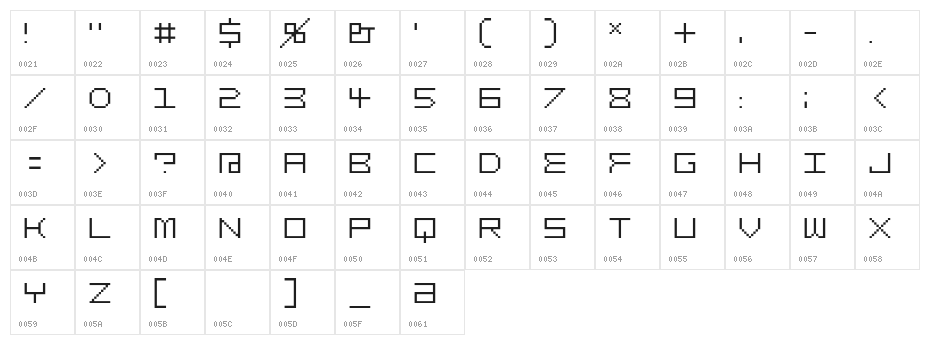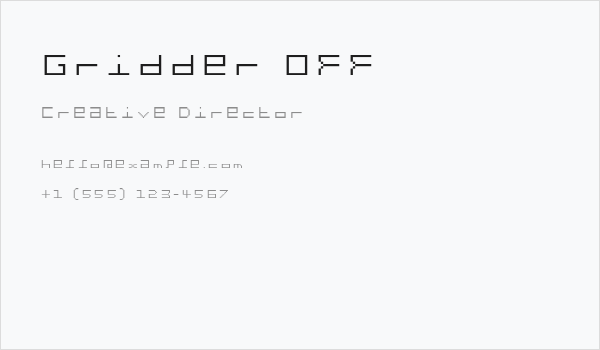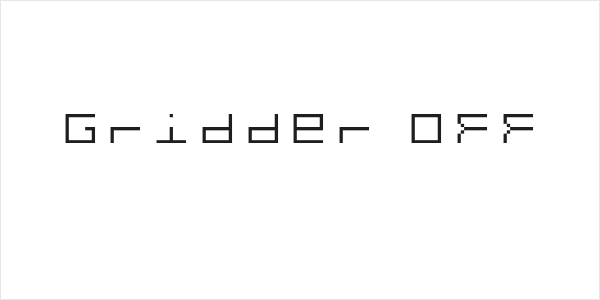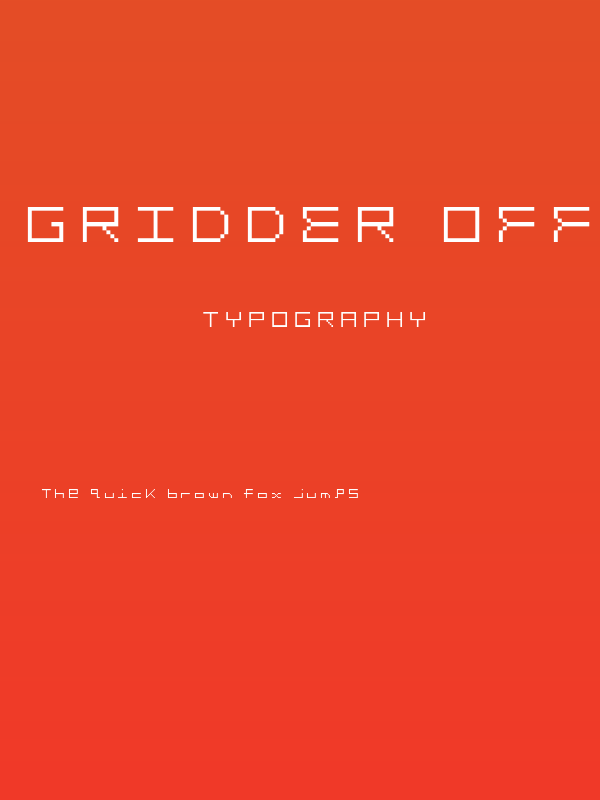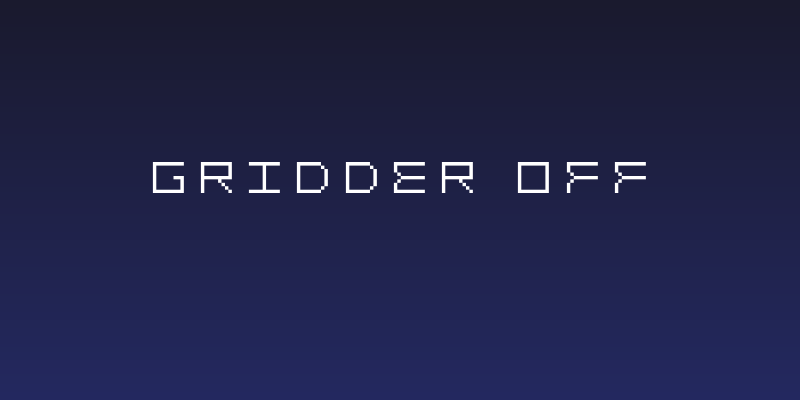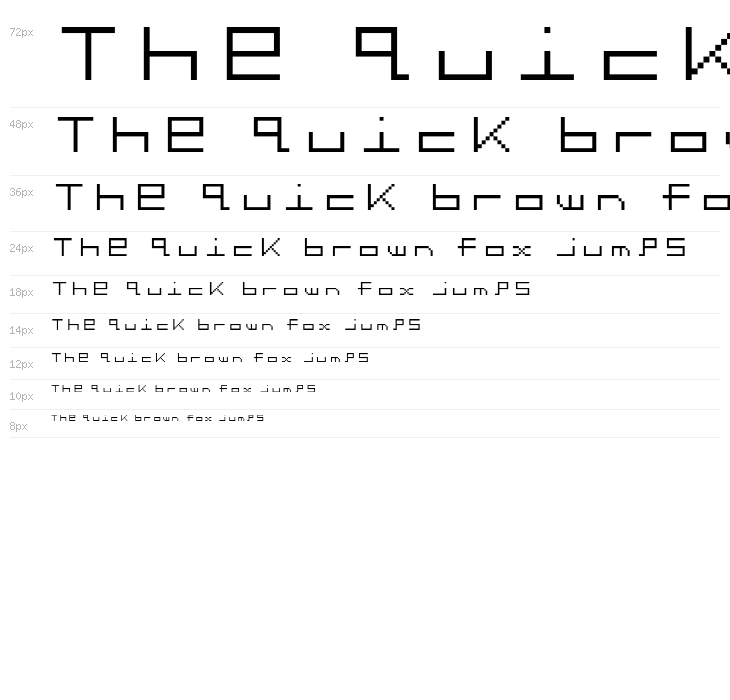
Gridder OFF Font
| Kategorien | Futuristic |
| Gesamtstil | Retro, Digital |
| Anwendungsfall | Headlines, Logos, Digital Art |
| Vorgeschlagene Projekte | Ideal for retro video games, tech-themed designs, digital art projects, and any creative work that seeks to evoke nostalgia for early computer graphics. |